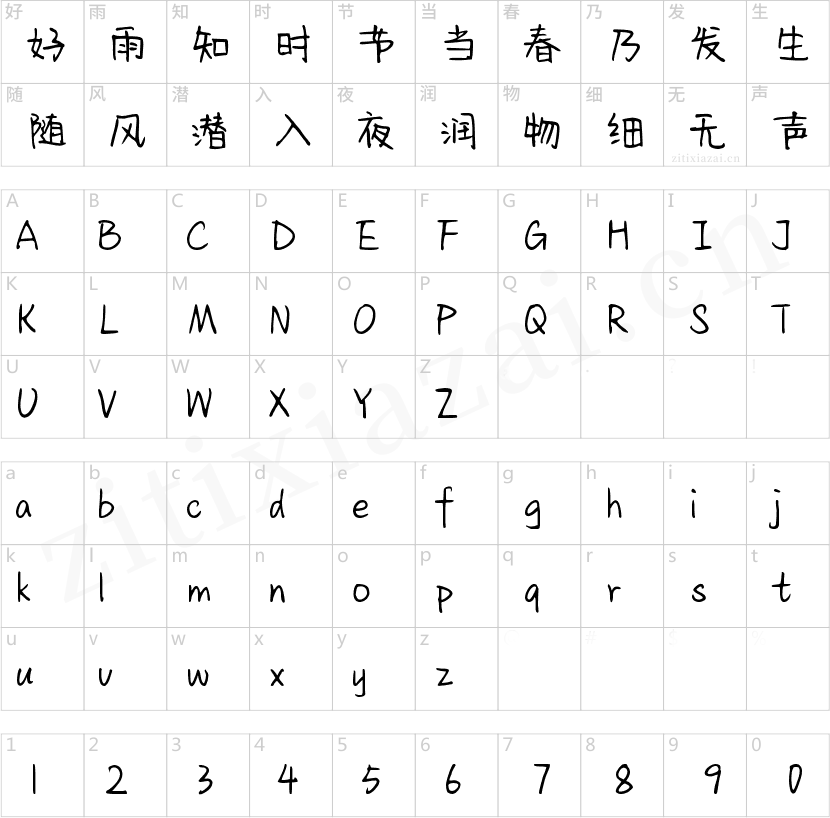
Aa白衬衫旧巷尾
Aa白衬衫旧巷尾,这款字体结构工整、笔画清晰,兼顾美观与易读性,适用于标题、正文、海报、包装、LOGO 等多种场景。字形优雅稳定,风格百搭耐看,适配日常排版与创意设计,让文字呈现更舒适、更具质感。Aa白衬衫旧巷尾一笔一画,皆是细节,以均衡的比例、流畅的线条打造舒适视觉体验,字形端正大气,风格简约现代。无论是商业设计、品牌宣传还是日常排版,都能轻松驾驭,让文字更有格调与力量。Aa白衬衫旧巷尾字体下载。
Aa白衬衫旧巷尾是一款非常具有艺术性的字体,它的设计灵感来源于对古典艺术的研究,同时又融入了现代字体设计的元素。字形优美,笔画粗细变化自然,给人以大气、典雅的感觉。Aa白衬衫旧巷尾是一款既传统又现代的字体,它的设计充满艺术感,美观大方,实用性也非常强。无论是对于设计师还是对于普通读者来说,都是一种非常不错的字体选择。Aa白衬衫旧巷尾适合用于具有艺术感的场合,比如海报、宣传单张、书籍封面等。由于其字形流畅且具有动态感,也适合用于大量的文本排版,如报纸、杂志等。